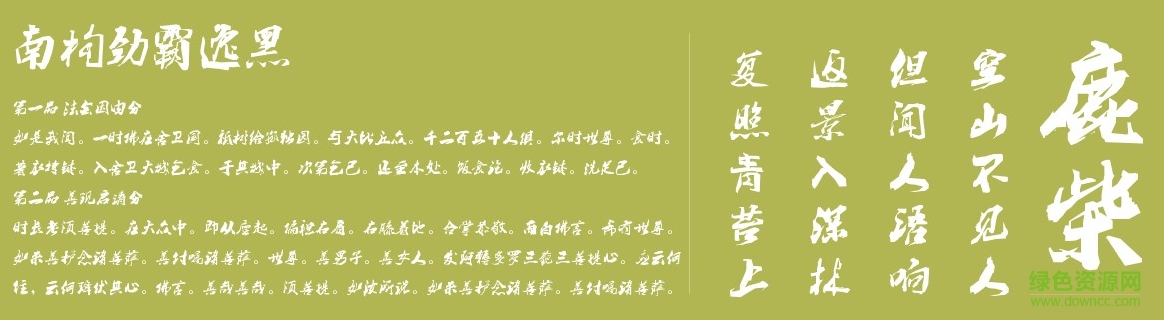
南構(gòu)勁霸逸黑體是一款南構(gòu)字體出品的黑體字體,行草風(fēng)格自帶霸氣,筆力遒勁,以手潑墨,然后揮筆撒就。適用于文章標(biāo)題、廣告門牌等等。歡迎大家來綠色資源網(wǎng)下載使用!
南構(gòu)勁霸逸黑是一款具有強(qiáng)烈視覺效果的黑體行草風(fēng)字體,筆畫之間帶有一種霸氣和鋒芒,給人以陽(yáng)剛之氣,充滿力量和飽滿感,是一款不錯(cuò)的標(biāo)題字體。